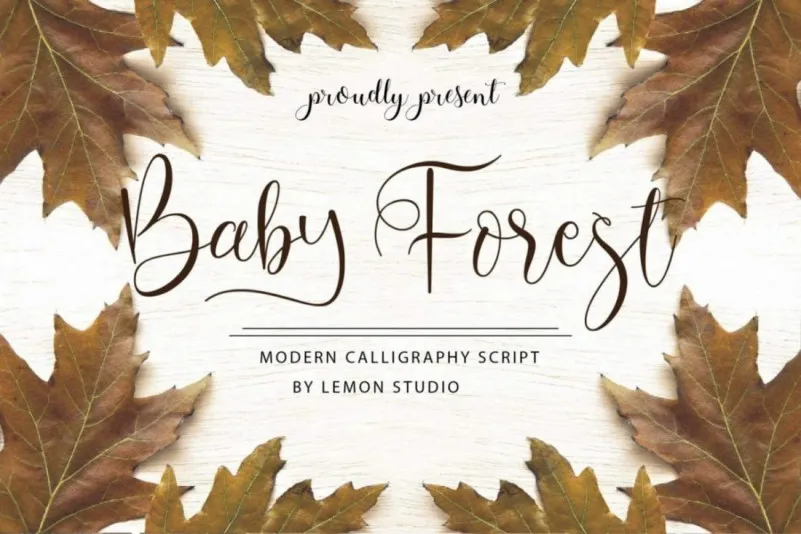
A “Baby Forest Font” é uma elegante e assertiva fonte escrita, perfeitamente projetada pelo Lemon Studio para transformar qualquer projeto em algo extraordinário. Esta fonte se destaca não apenas pela sua beleza única, mas também pela sua versatilidade. Ela está disponível para uso em uma variedade de formatos, incluindo títulos, logomarcas, cartões de casamento, camisetas personalizadas, assinaturas, sinalização, rótulos, capas e até mesmo na criação de materiais publicitários como cartazes e etiquetas. Além disso, a fonte oferece um leque variado de características alternativas para uso em diferentes contextos. Estas incluem alternativas estilizadas que permitem um toque personalizado, swashes para dar vida aos caracteres, números de estilo moderno, e funções de pontuação que a tornam ainda mais versátil. É uma escolha perfeita para quem busca uma fonte escrita criativa e única.